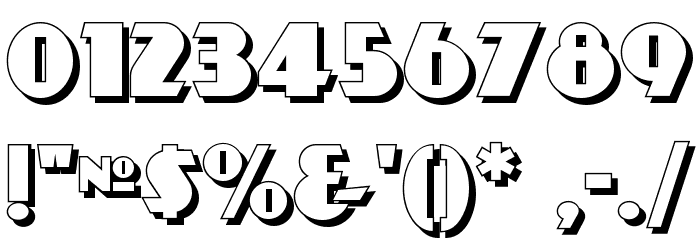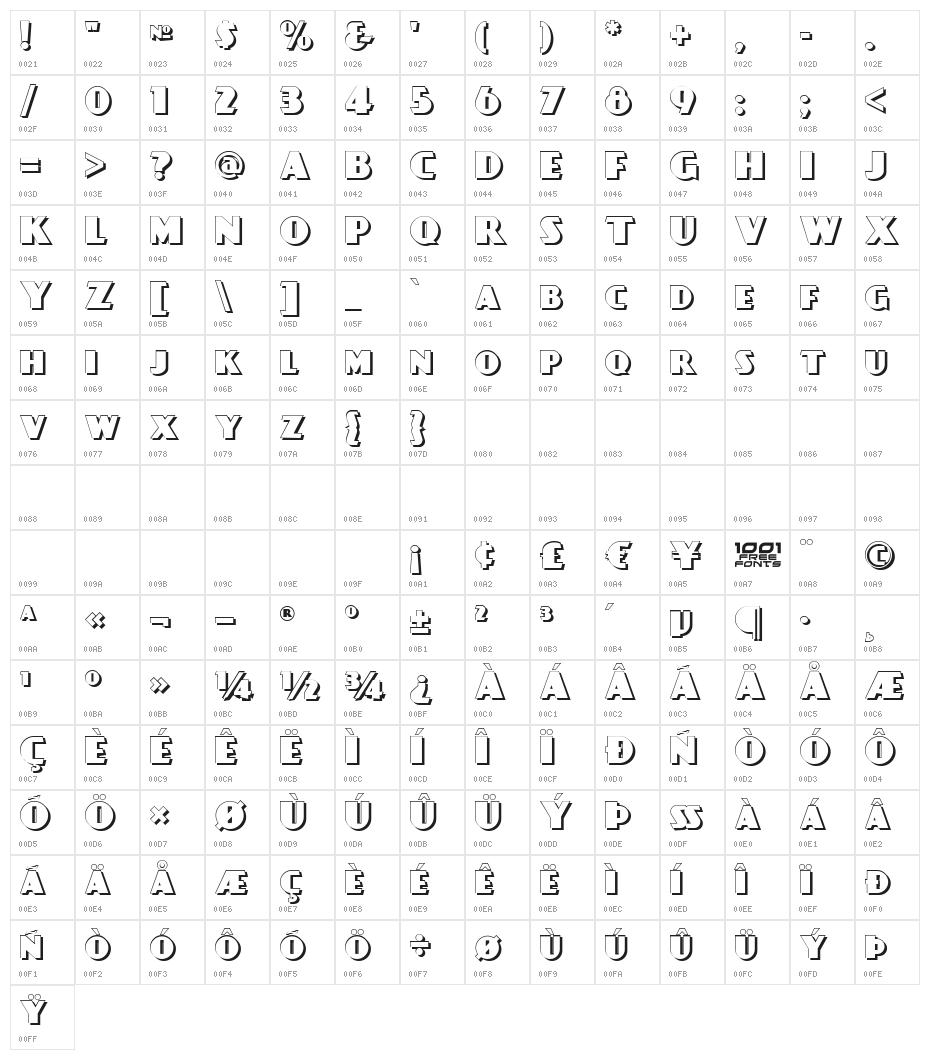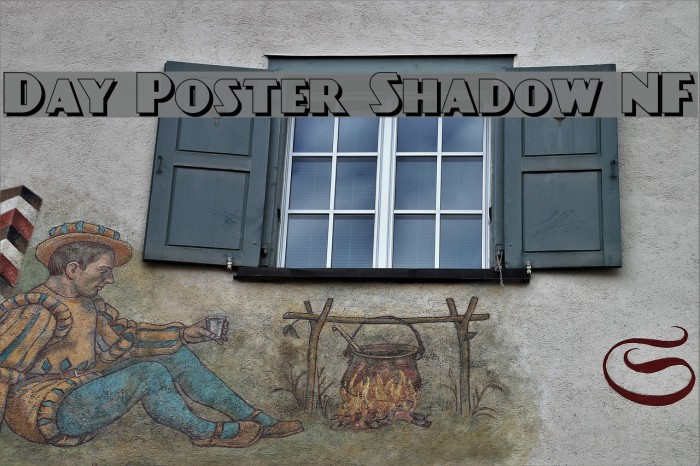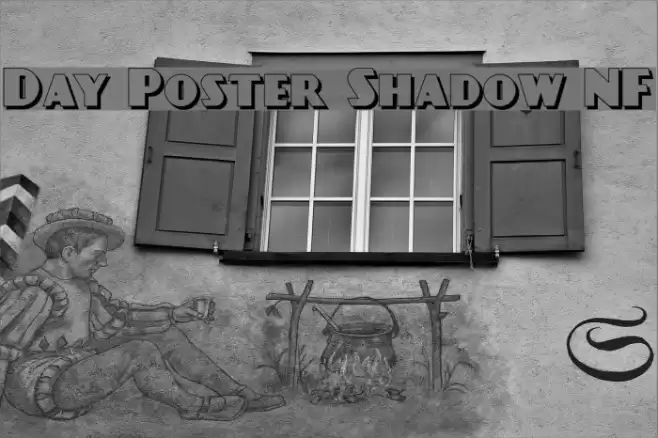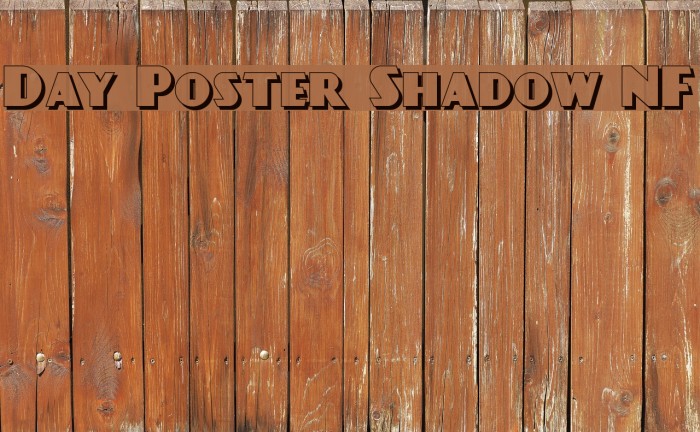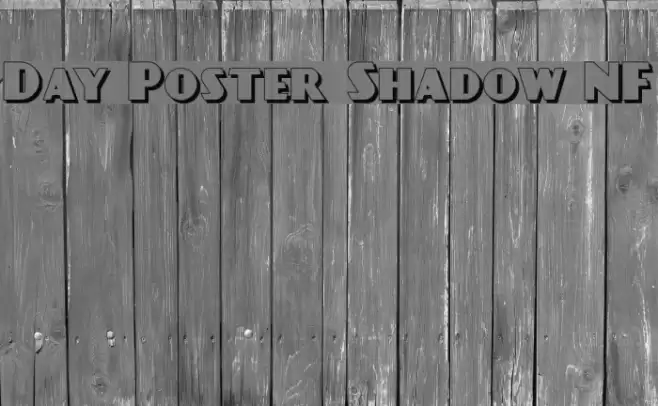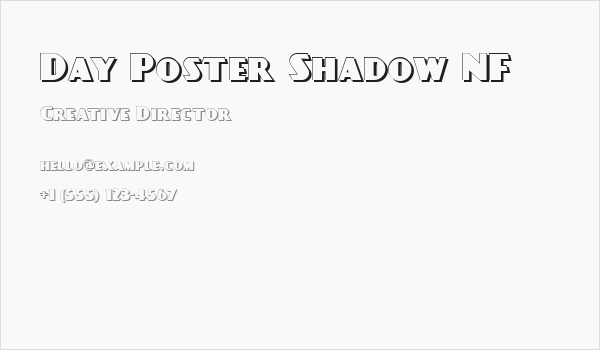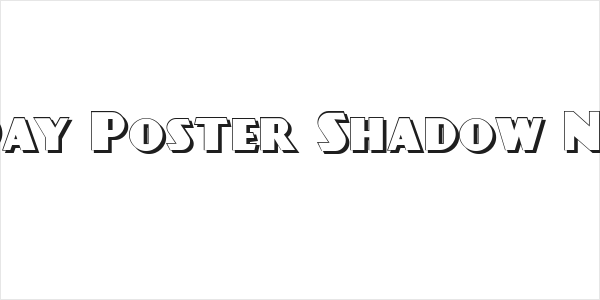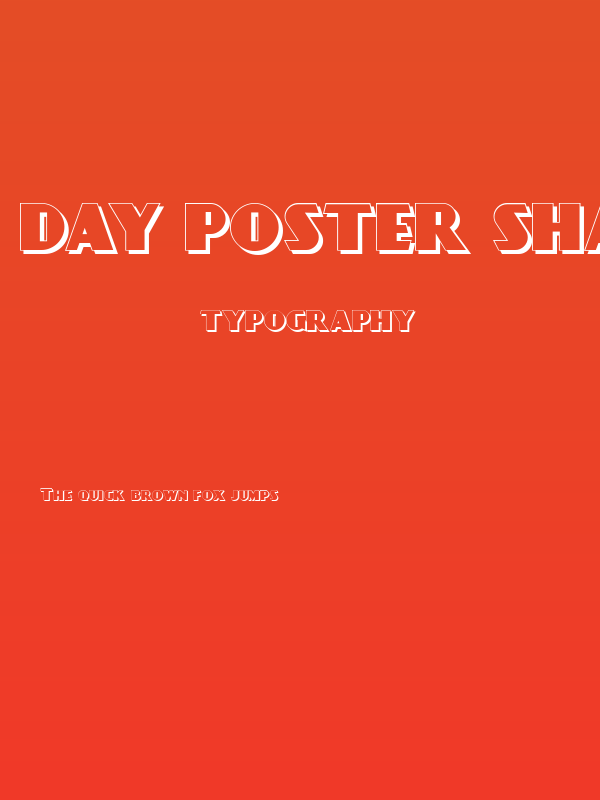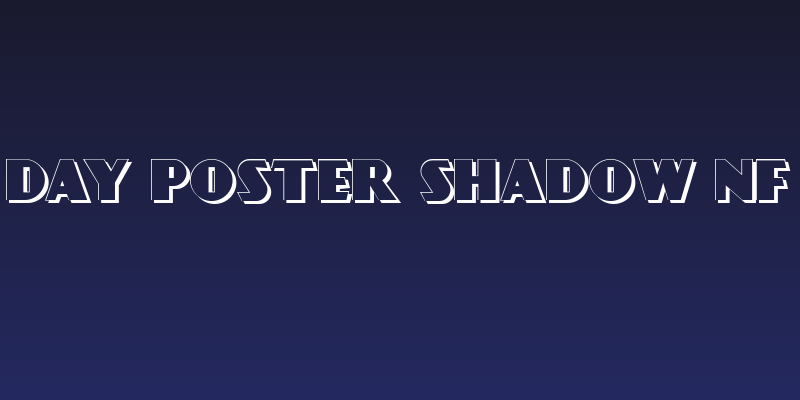
Day Poster Shadow NF Font
| Cas d'utilisation | Headlines, Posters, Logos |
| Projets proposés | Ideal for poster designs, retro-themed graphics, advertising, and branding projects that require a strong visual impact. |